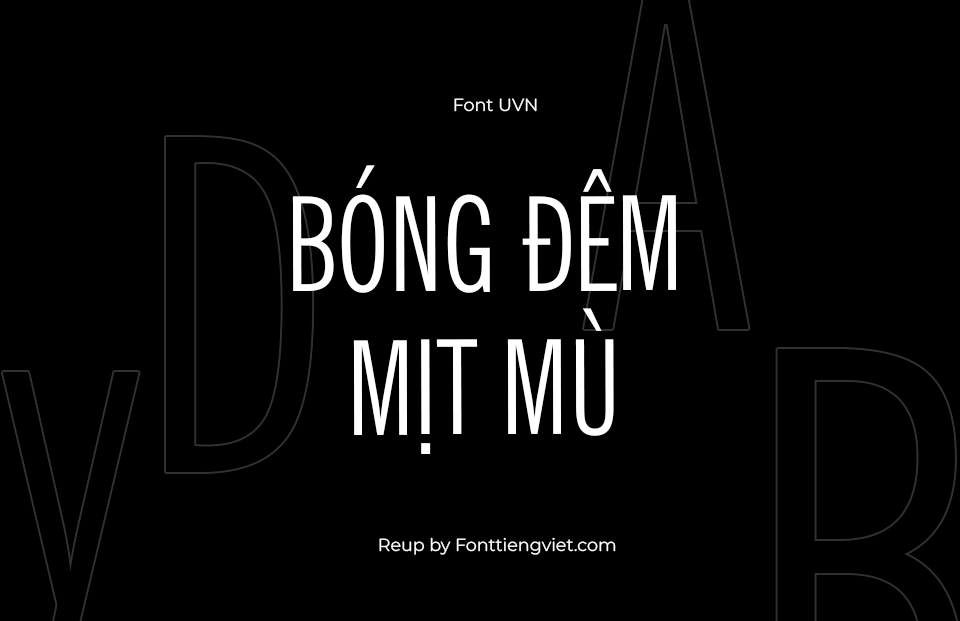
Tải Font Việt Hóa UVN Tin Tuc Hep Them Miễn Phí Cho Thiết Kế Báo Chí
Giới thiệu về Font Việt Hóa UVN Tin Tuc Hep Them
Trong thế giới thiết kế đồ họa chuyên nghiệp, việc lựa chọn Font Chữ phù hợp đóng vai trò quyết định đến tính thẩm mỹ và khả năng truyền tải thông điệp. Font Việt Hóa UVN Tin Tuc Hep Them là một trong những bộ phông chữ đặc biệt được tối ưu hóa riêng cho lĩnh vực báo chí và trình bày văn bản có độ dài lớn. Với cấu trúc các ký tự được thu hẹp về chiều ngang, bộ phông này giúp tiết kiệm diện tích dàn trang mà vẫn đảm bảo sự rõ nét tuyệt đối cho người đọc.
Ưu điểm nổi bật của font chữ UVN
Đặc điểm lớn nhất của Font Việt Hóa UVN Tin Tuc Hep Them chính là sự gọn gàng và hiện đại. Khác với các kiểu chữ thông thường, dòng phông này loại bỏ các chi tiết thừa, tập trung vào độ thanh mảnh và cao ráo. Điều này giúp các em học sinh dễ dàng sử dụng để làm báo tường, thiết kế slide thuyết trình hoặc trình bày các tiểu luận khoa học một cách chuyên nghiệp hơn. Hệ thống dấu tiếng Việt được căn chỉnh chuẩn xác, không bị lỗi hiển thị trên các phần mềm phổ biến như Word, Photoshop hay Illustrator.
Cách ứng dụng Font Việt Hóa UVN Tin Tuc Hep Them hiệu quả